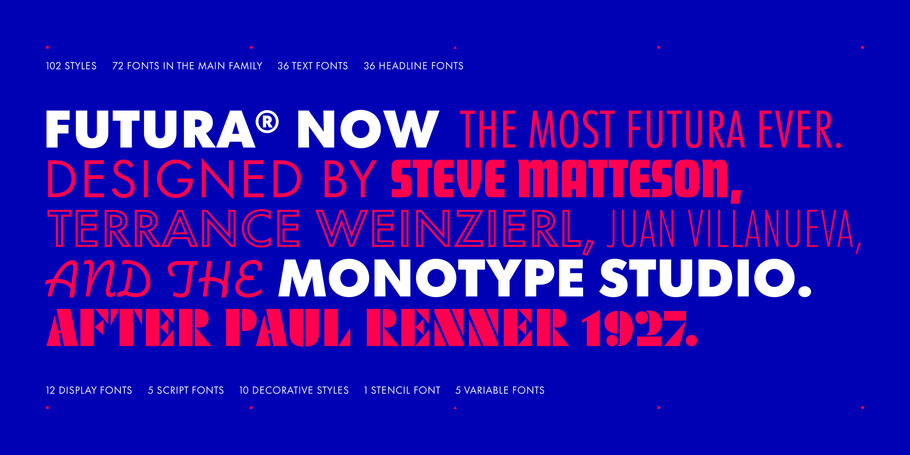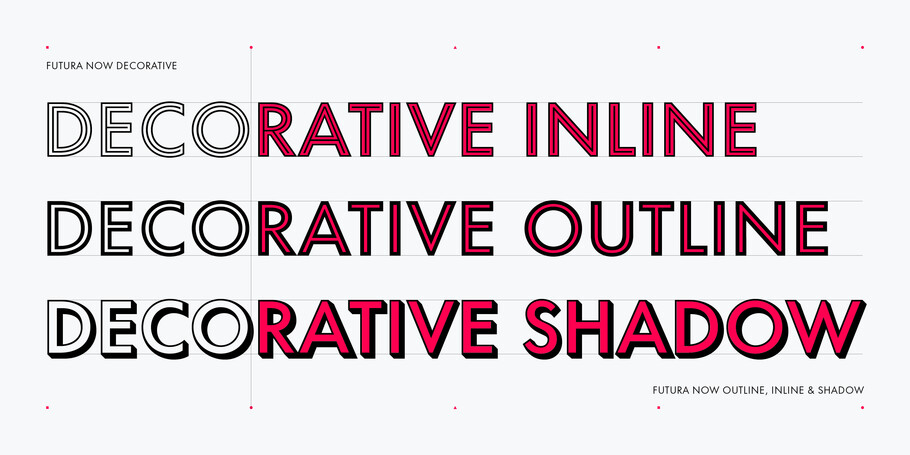
Presentamos Futura Now: La versión definitiva de una familia emblemática.
« Futura Now es justamente lo que Futura necesitaba para poder seguir presente en el exigente mundo tipográfico actual, y cuenta con una paleta de grosores contemporánea y archivos de fuentes variables para obtener interpolaciones infinitas. »
Futura Now es la versión definitiva de la letra de palo seco geométrica por excelencia. Esta versión redigitalizada de los diseños originales de Paul Renner se ha actualizado para ofrecer una paleta tipográfica más contemporánea.
En este lanzamiento se incluyen 102 estilos (incluidos los grosores Condensed, Headline y Text), así como una compatibilidad con idiomas nunca vista. Futura Now también ha reeditado las fuentes Display y Script que, aunque menos conocidas, también pertenecen a la familia Futura.
Futura ha gozado de una popularidad incesante en los 90 años que han pasado desde su lanzamiento. La fuente ha estado muy presente en revistas de moda, discos y películas emblemáticas, paneles de instrumentos e incluso en la placa que los astronautas colocaron en la luna en 1969. Generaciones y generaciones de principiantes en el diseño gráfico han aprendido a utilizar los tipos gracias a Futura. Su calidez atemporal, su austeridad y la astuta combinación de proporciones geométricas y clásicas que la caracteriza siguen siendo igual de relevantes para las marcas actuales. No es exagerado afirmar que Futura es la letra de palo seco geométrica por excelencia, un icono sin rival en el mundo tipográfico.
Sin embargo, el paso del tiempo y los rápidos cambios que se han producido en la tecnología de la composición tipográfica no siempre han sido positivos para Futura. No todas las actualizaciones de las versiones digitales de este tipo de letra son fieles a la fuente original (pensemos que las fotocopias de las fotocopias pierden calidad gradualmente). Como resultado, muchos diseñadores y diseñadoras que creen que llevan años trabajando con Futura, en realidad pueden haber estado trabajando con una aproximación alejada del diseño original.
Este era uno de los problemas que Steve Matteson, director creativo de tipos de Monotype, quería solucionar. Futura Now recopila, organiza y reelabora toda la historia de la familia Futura, desde los esbozos iniciales de Paul Renner hasta los tipos de fundición de metal lanzados por Bauer y las hermosas páginas de muestra que acompañaron al lanzamiento de Futura. Es el resultado de un minucioso proceso de estudio, planificación y elaboración, que va mucho más allá del resurgimiento histórico.
«El reto consiste en vislumbrar cómo los diseños atemporales pueden beneficiarse del perfeccionamiento contemporáneo», explica Matteson. «Estamos mejorando los atributos de la fuente original y ampliando sus capacidades para adaptarla a los tiempos actuales».
Futura Now es justamente lo que Futura necesitaba para seguir presente en el exigente mundo tipográfico actual. Resuelve el espaciado incoherente de versiones digitales anteriores y revisa la gama de grosores y la nomenclatura del tipo de letra; es decir, el estilo Ultra Bold es tan potente y el Thin tan delicado como cabría esperar de sus nombres. Futura Now también recupera la cursiva verdadera, para dejar atrás las redondas inclinadas y oblicuas, presentes en otras versiones. (Las oblicuas se crean inclinando el diseño vertical original, lo que hace que las formas se distorsionen. Las cursivas de Futura Now se mantienen fieles al original y preservan el ritmo geométrico del diseño).
El lanzamiento presenta una paleta contemporánea de grosores (incluidos los archivos de fuentes variables para obtener interpolaciones infinitas de grosor y anchura) y compatibilidad con idiomas para adaptarse a un mayor número de sistemas de escritura, incluidos los alfabetos griego y cirílico.
Futura Now también vuelve a introducir parientes menos conocidos del diseño original de Renner. Futura Now Display es una fuente rectangular-geométrica que contrasta de forma impactante con la familia principal de Futura. Por otra parte, Futura Now Script, diseñada originalmente por Edwin Shaar, es una interpretación monolineal de la escritura a mano, cuyo objetivo es generar un suave contraste con la austera geometría de Futura.
Partiendo de las muestras de Bauersche Gießerei, una fundición tipográfica, el equipo de diseño de Monotype examinó minuciosamente las formas, la proporción y el espaciado de los caracteres, y recuperó detalles que se habían perdido durante los años de su declive digital. En diseños geométricos modernos, como Avant Garde, se incrementó el tamaño de las minúsculas en relación con las mayúsculas, lo que hizo que se perdiera la elegancia de las proporciones de Futura. Las versiones para fotocomposición de Futura solían comprimir las formas de las letras para los tamaños de visualización, por lo que los tamaños de cuerpo de texto eran prácticamente ilegibles.
Para Matteson, que ha liderado al equipo de diseño de Futura Now, esta es la oportunidad perfecta para que muchos diseñadores y diseñadoras puedan evaluar realmente el tipo de letra original, en lugar de las digitalizaciones de hace 30 años con las que es probable que hayan trabajado en el pasado. De hecho, según Matteson, el nuevo lanzamiento aporta una humanidad muy necesaria al mundo de las letras de palo seco geométricas.
«Tiene un punto de calidez que queda bien en entornos orgánicos», explica. «Puedes colocar a Futura al lado de un árbol frondoso o de una mesa de acero inoxidable. Queda bien en ambos casos porque se sitúa, hábilmente, en la frontera entre la geometría superlimpia y la calidez humanista. Muchas geometrías contemporáneas parecen dibujadas con escuadra y cartabón, sin tener en cuenta detalles ópticos y ergonómicos».
Matteson añade: «Es importante tener en cuenta los elementos humanos de la tipografía y la comunicación, sobre todo en los tiempos que corren».